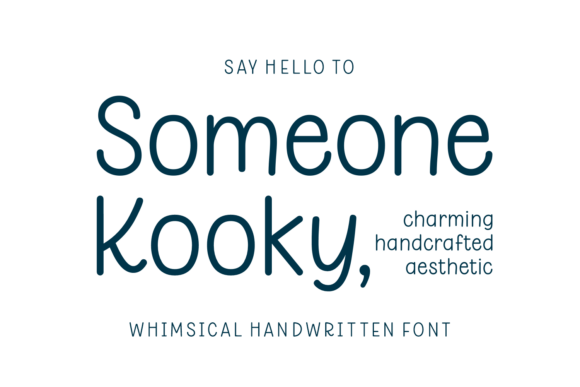
Someone Kooky
適切なデザイン要素を見つけるのは難しい場合がありますが、Someone Kookyは作品を即座に引き立てる優れたコレクションを提供します。
POD(オンデマンド印刷)製品、結婚式の招待状、またはソーシャルメディアのグラフィックを作成している場合でも、Someone Kookyは理想的です。